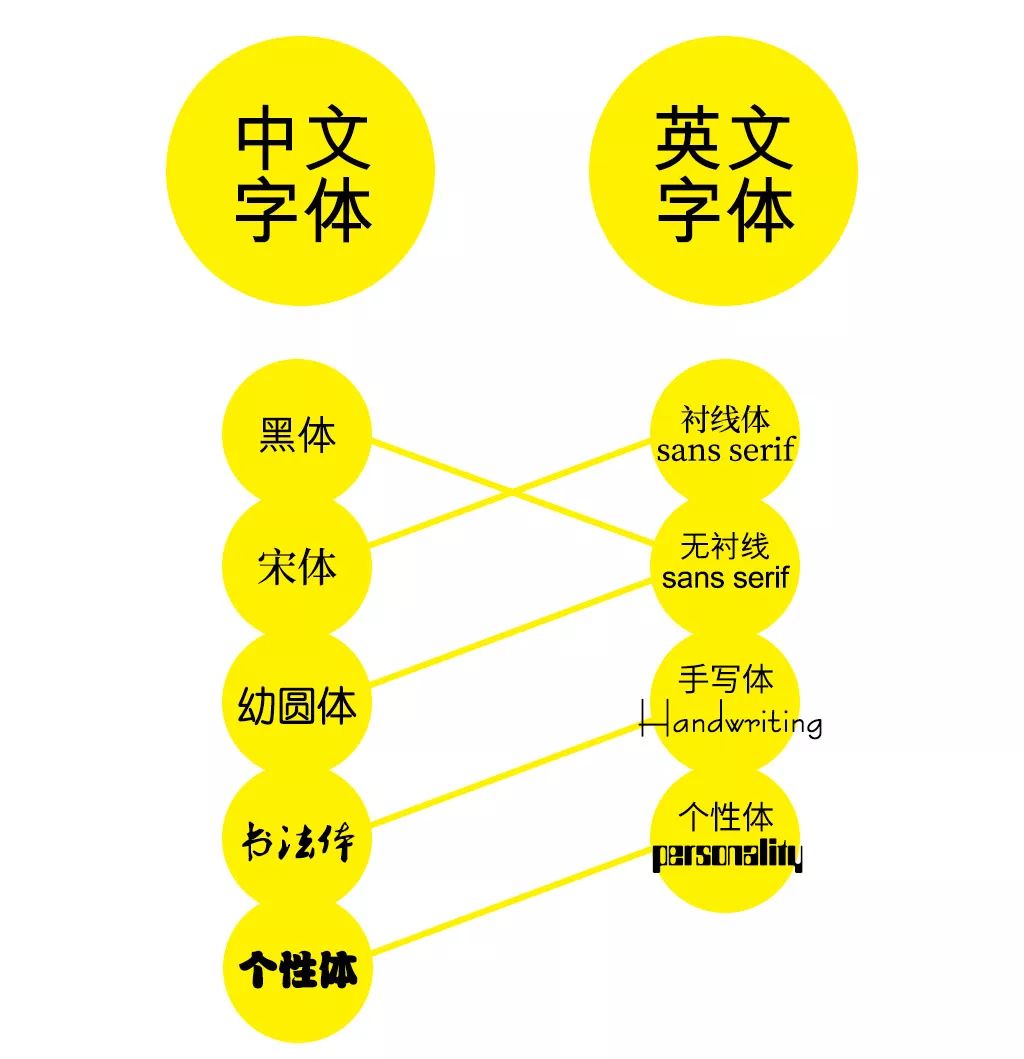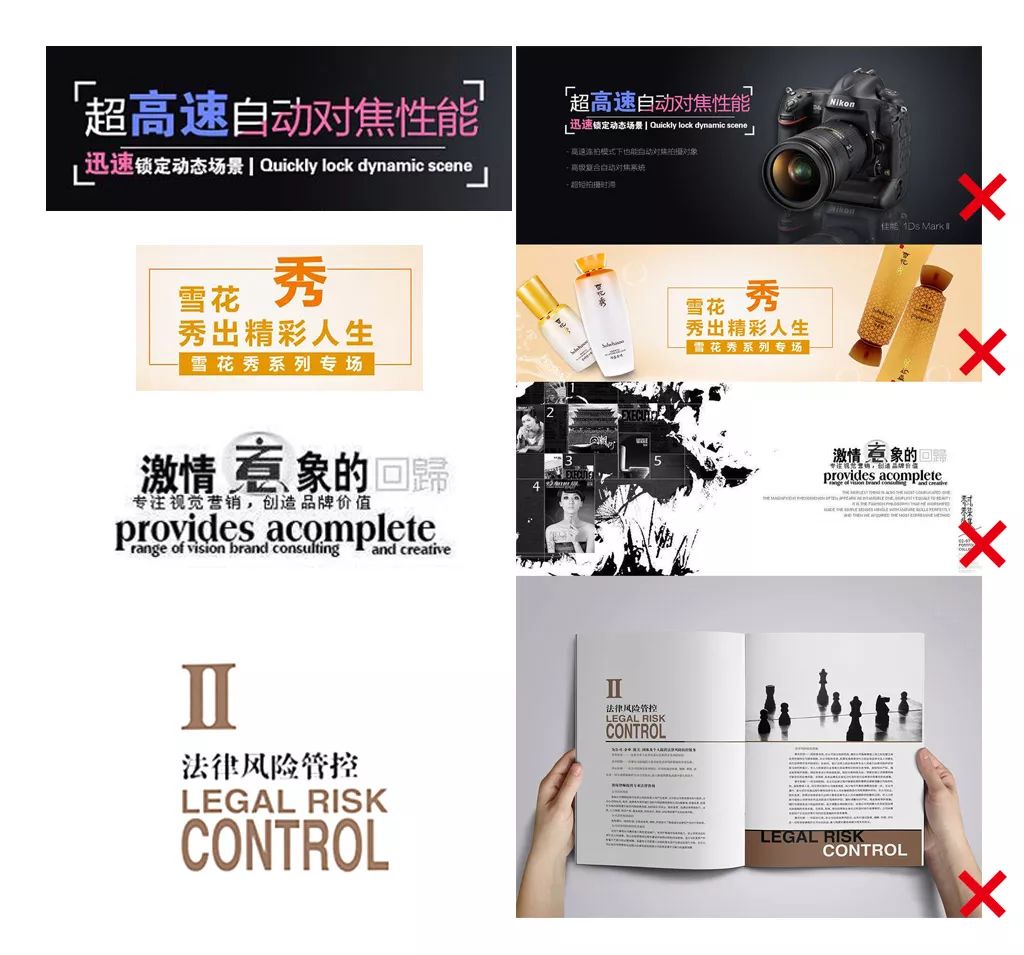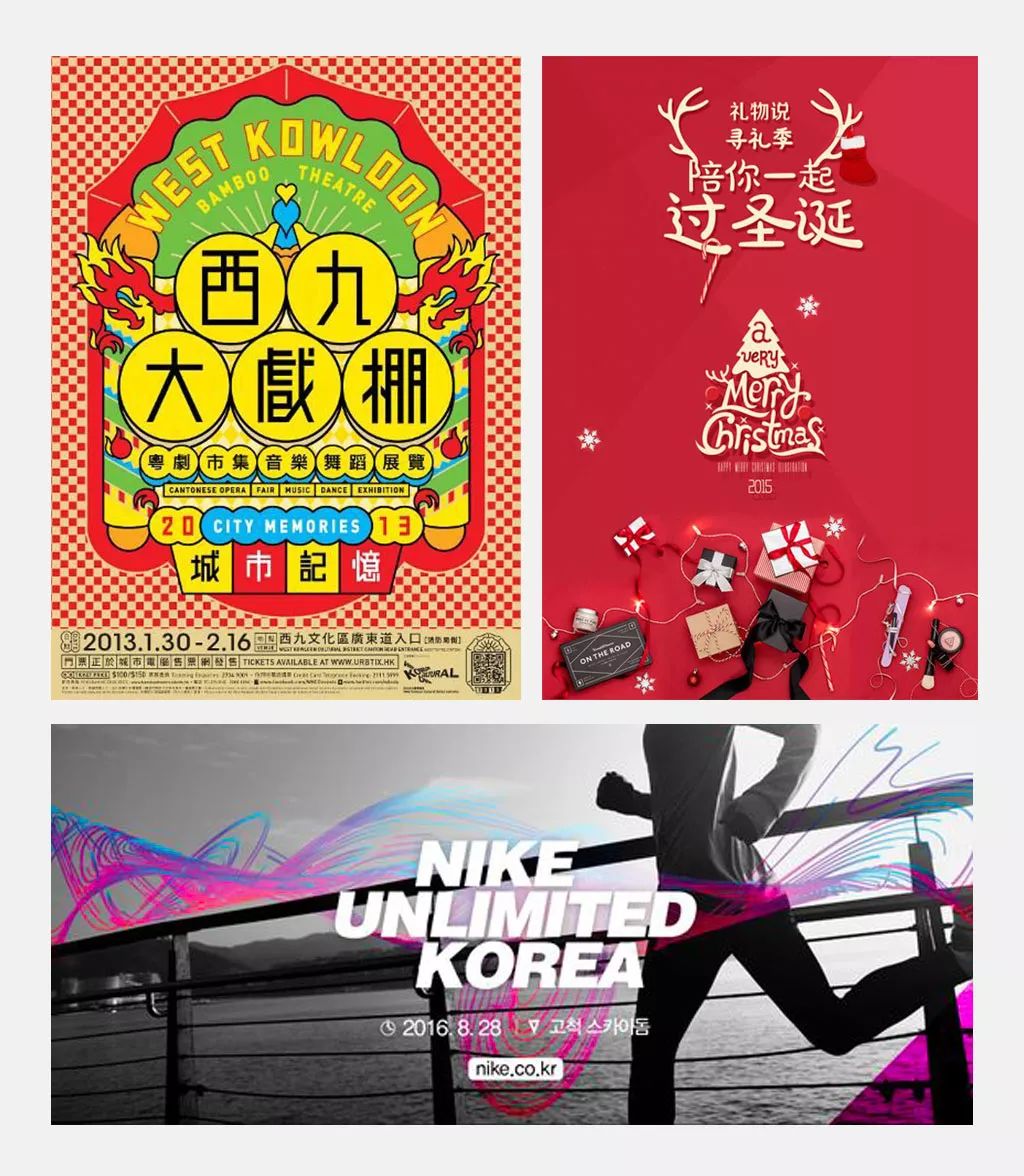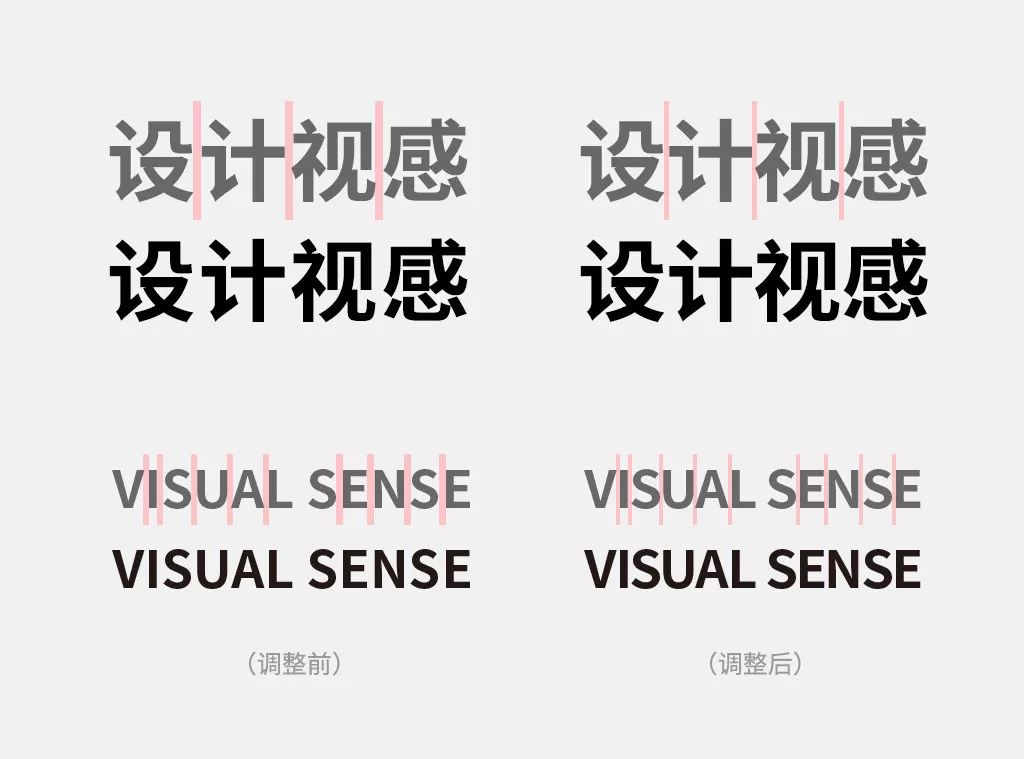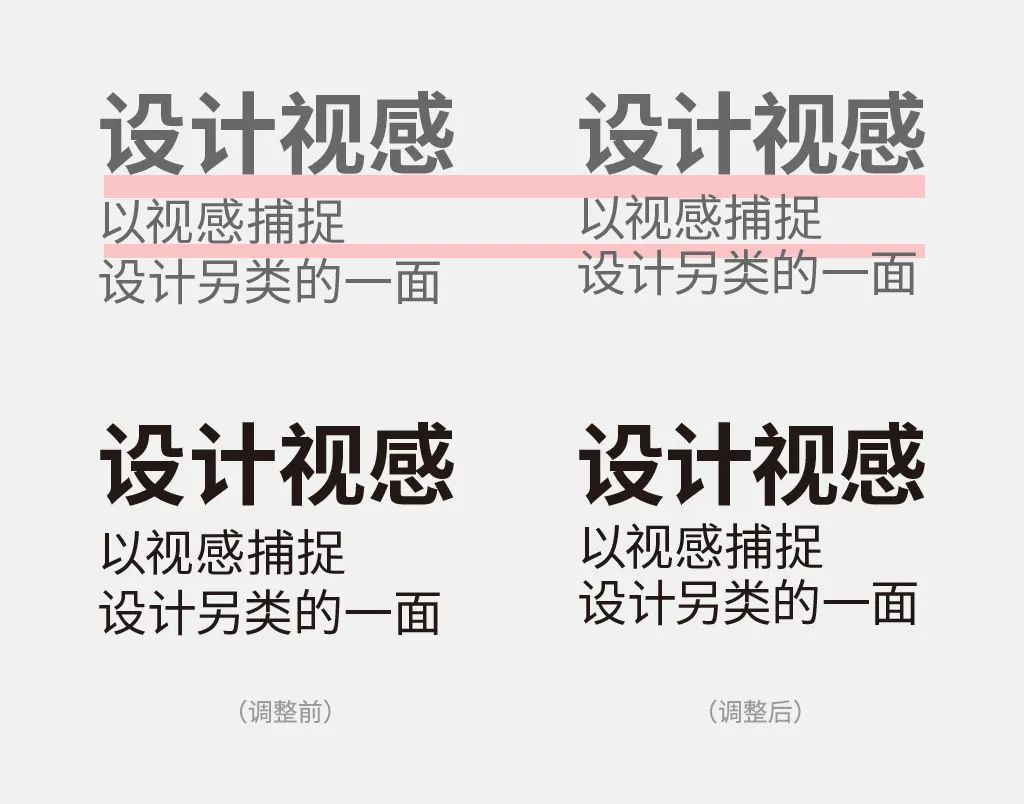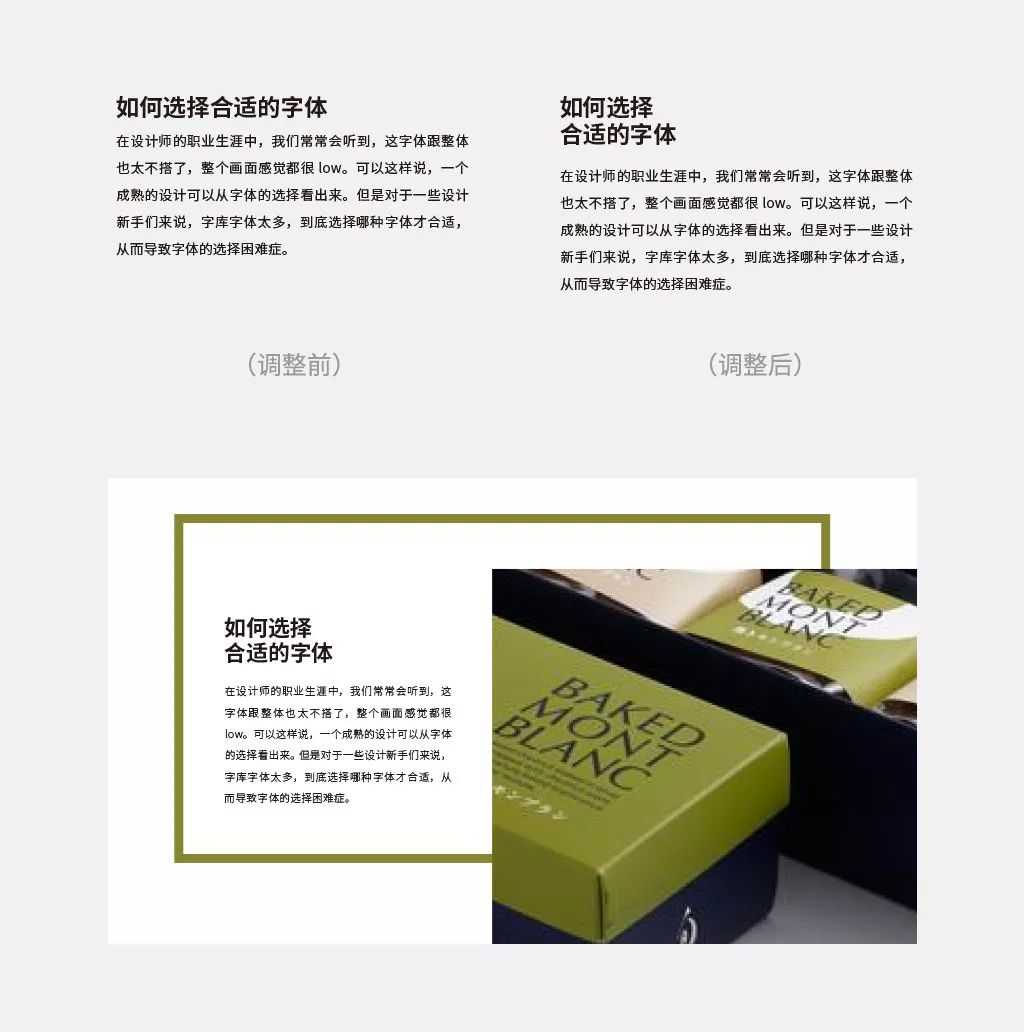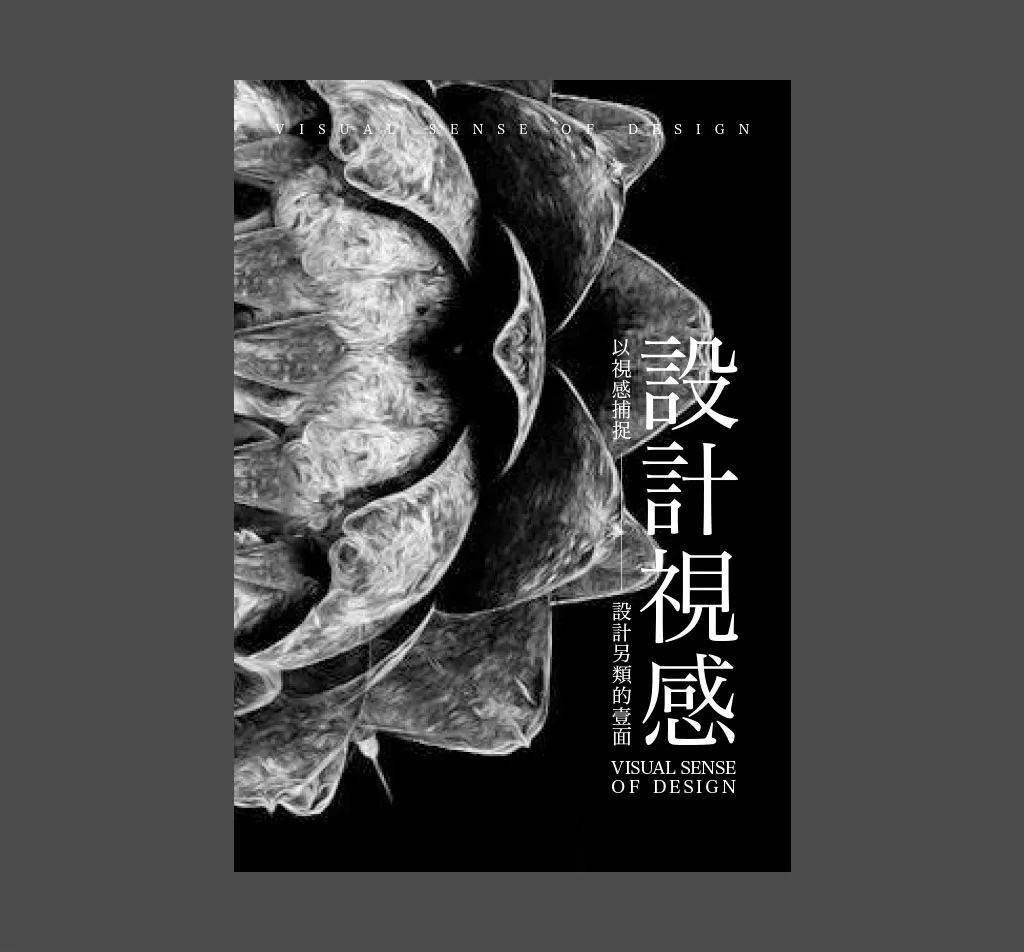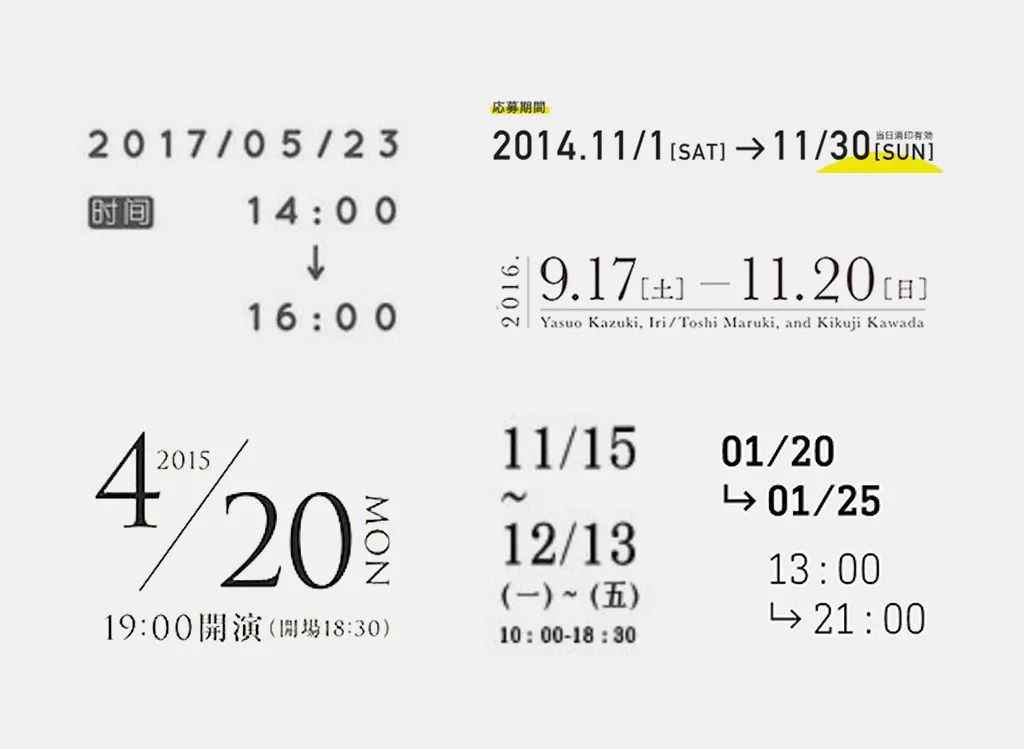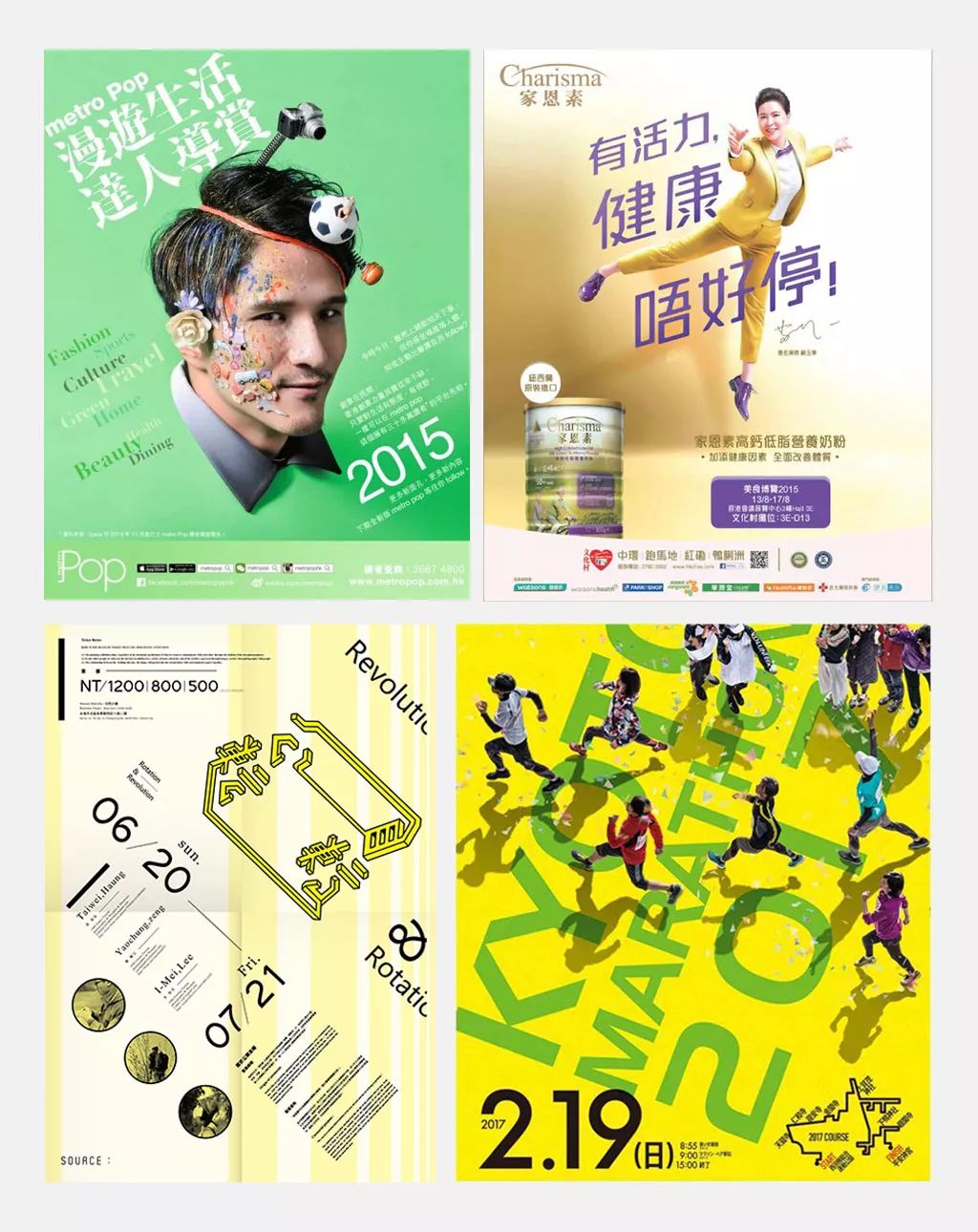
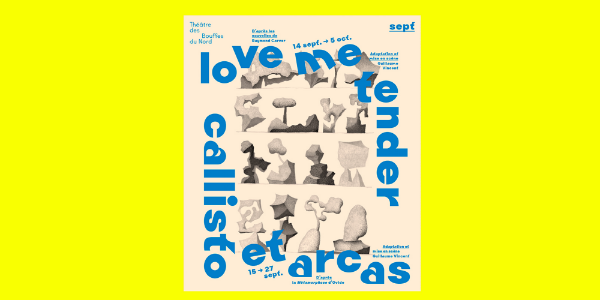
学会这套标题排版,谁还敢说你设计low?
今天我们来说说标题排版,很多人不重视这块,觉得只要把文字信息放上就行了,然后就杯具了……
都不知道是层级错误、字体不符造成的问题,so你离成熟的设计还差几步?
首先字体的选择很重要,跟整体不搭的话,会导致画面low爆,所以你要从字体类型>字体气质>不超过3种,一步步入手。
字体组合
选好了字体,就要开始组合了,标题的功能是短时间内能让读者快速了解信息,所以一定不能单调,下面有4种类型。
中+中
粗体的可作为标题,细体可作为正文。为了让中文+中文的组合不单调,可以从简单对比,甚至添加元素,使组合更有层次感。
英+英
跟中+中搭配基本类似,也是通过对比的方式,强调标题的层次感。
英+中
到了英文和中文的组合,就比之前复杂了,所以一定要注意文字间的张弛有序。
数+中/英
添加数字后,会形成两个小方块,使文字逻辑更清晰。
字体编排
知道选啥,怎么组合,依然容易使画面杂乱不堪,是不是犯了下面这四个问题?
字体的搭配
必须考虑消费群体,并不是每个人都能看懂你的设计,所以不要使用过于花俏的字体,除非是为画面设计的定制字体。
间距的调整
对于入门设计师来说,通常都会选择默认的间距。但是不同的字体,产生的行字距都不一样。所以需要反复调整,直到视觉上舒适。
层级的变化
清晰的层级关系是信息传达的基础,简单来说就是,哪里重要就突出哪里。
只是通过简单的大小对比,就把层级明显区分开了。
再加上颜色对比和添加细线,设计感就强烈了很多。
文本的断行
标题的文字不宜过多。如果非要使用较多文字,那就要学会断行,这样不仅提高阅读效率,还能形成文本断行后的留白效果。
标题套路
学完了基本方法,下面看几个实战套路~
横编排
竖编排
横竖编排
错位编排
倾斜编排
非对称的画面形式,使版面具有动感。
叠压编排
可以看作图+字、字+字、字+元素等形式,使画面表现力更丰富。
线框编排
将文字与线框结合,也是老生常谈了,只是要注意粗细和长度,考虑它们之间的关系,并非随意添加。
肌理编排
想让标题带来意境感,就要合理运用肌理。
时间编排
在做海报的时候,经常会遇到时间信息的编排,所以可以作为二级信息出现,一般月日层级最高,其次是具体的钟数,最后是年份。
价格编排
如果遇到促销打折的情况,要善于利用数字和符号吸引消费者。比如把“五折”转换为“5折或50%off”,更直观明了。
以上的内容虽说都是比较容易掌握的技巧,但也要多多练习,把层级关系了然于胸,这样你的版面才会有的放矢。